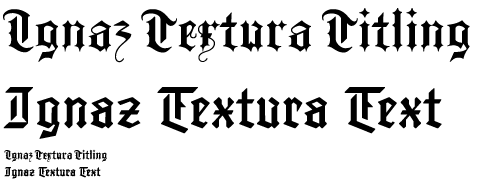
Die Ignaz Textura Schriftfamilie ist von der amerikanische Designer Dan Reynolds entwickelt. Beim Design der Schriftfamilie wurde er durch die Buchstaben eines Tableaus außerhalb der Kirche St. Ignaz in Mainz inspiriert. Diese Buchstaben, die im Jahr 1519 gemeißelt wurden, stellen eine neue Interpretation der Texturaform dar.
Buchstaben in Stein zu meißeln erfordert kleine Änderungen des Alphabets. Diese Änderungen, die in seiner Schrift zu sehen sind, bieten einen neuen Blickwinkel, der allerdings auch auf die unfassbare Geschichte der gebrochenen Schriften hinweist. Desweiteren ist es interessant, dass diese Buchstaben aus den letzen Tagen der Entwicklung der Texturaschrift stammen. Wegen Gutenburg und seinen Nachfolgern waren Texturas zu dieser Zeit immer noch die meistverwendete Schriftart in Mainz. 1519 entwickelten die Nürnberger Schriftkünstler, u.a. Albrecht Dürer, die Frakturschrift. Dies bedeutet zugleich das Ende der Textura-Ära. Nach der Veröffentlichung der Luther-Bibel im Jahr 1532—die in der Frakturschrift gesetzt war—bleibt die Frakturschrift fast die einzige offizielle Schrift in Deutschland, bis zum zweiten Weltkrieg.
»Ich finde, dass diese ältere Art von gebrochenen Schriften, nämlich die Textura, eine der vergessenen Teile der Geschichte der Schrift ist«, erklärt Reynolds. Seit dem Anfang der Digitalisierung, hat man ein neues Interesse für ältere Schriftarten wie die Fraktur entwickelt. Besonders in den USA entscheiden sich immer mehr Schriftgestalter dazu, mit ähnlichen Formen zu arbeiten. Mit Ignaz Textura möchte Reynolds seinen Beitrag zu diesem Dialog leisten.
Die Ignaz Textura Schriftfamilie enthält zwei Schnitte: die Ignaz Textura Titling ist für Headline- und Displaytexte ab 18 Punkt geeignet, die Ignaz Text für Fleißtext von sechs bis 17 Punkt.